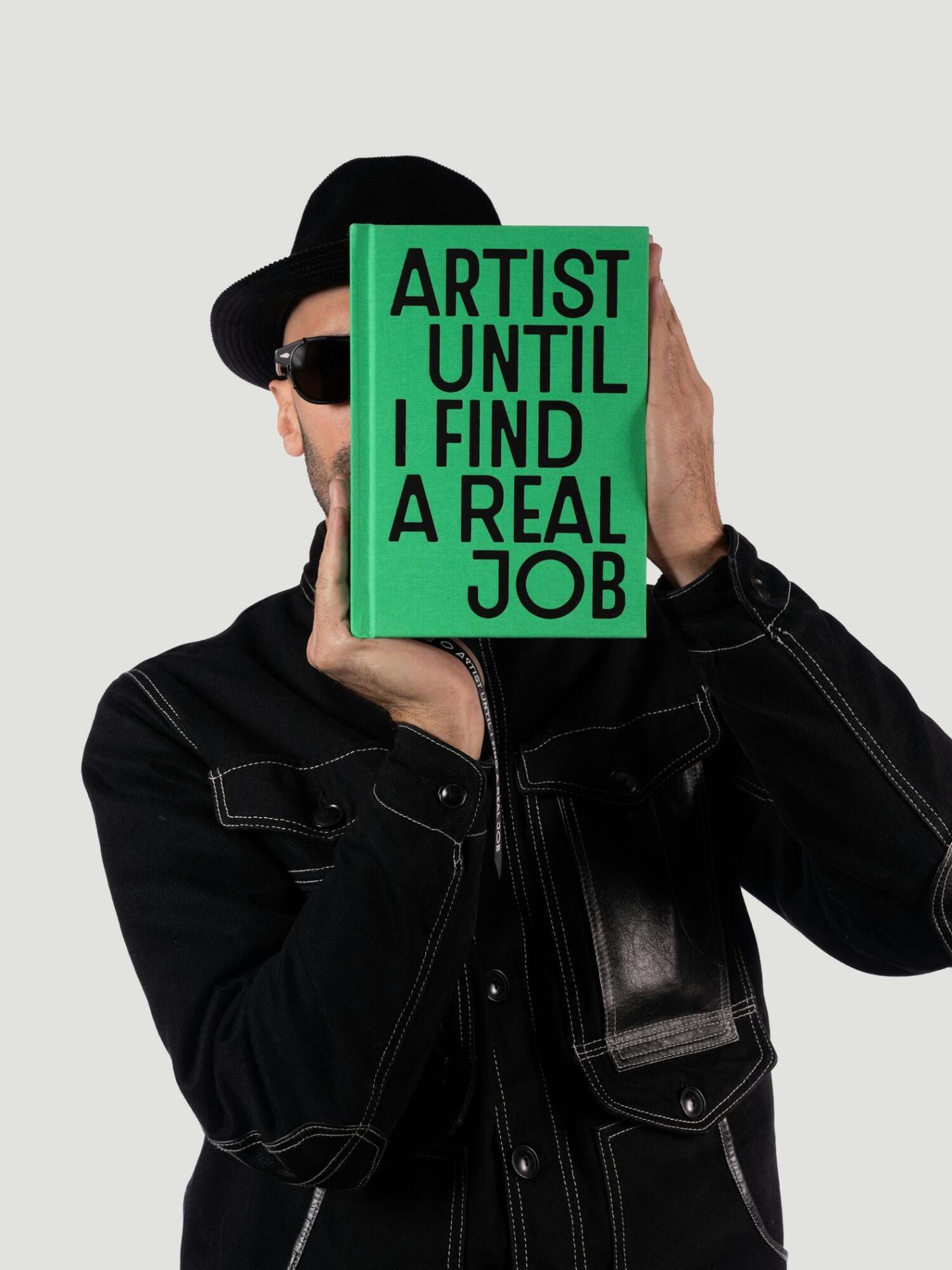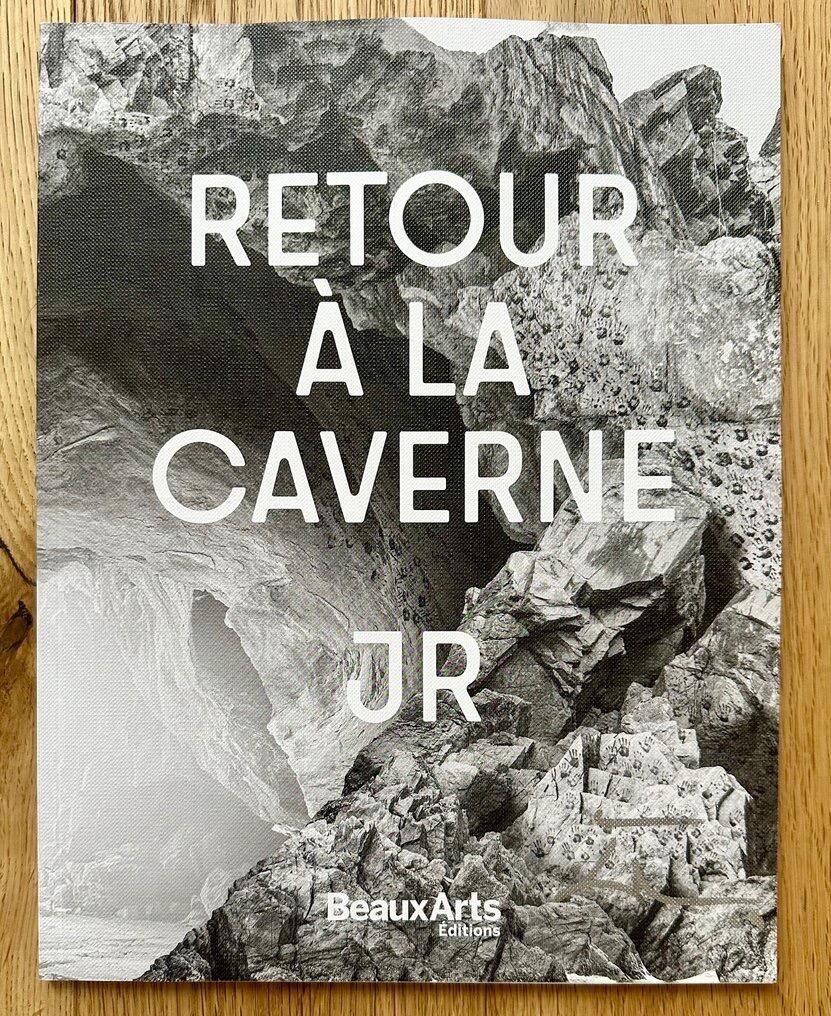
Schrift in Publikationen von JR (Artist)
Vermutlich eine Art Hausschrift für den Künstler – die Website sagt sie heißt »JR« (surprise!).
Die Frage ist von wem sie stammt und ob sie auf einem Retail-Font basiert ...
Die unterschiedlichen Varianten sind ja Konzept und technisch ist das ja auch kein Problem.
Arthur Alazard auf Instagram: »JR Type is a custom typeface designed with @h5paris for @atelierjr !«
Auf deren Website: »H5 gestaltet die Identität des Künstlers JR und seiner Online-Boutique Atelier JR. Unsere Antwort dreht sich um eine maßgeschneiderte Typografie, die von Emailleschildern und Buchstabenmalern inspiriert ist. Das berühmte Wort „Défense d’afficher loi du 29 juillet 1881“ (Verbot des Plakatierens, Gesetz vom 29. Juli 1881) wird echoartig dargestellt.
Die Darstellung des Auges, die in seiner Arbeit allgegenwärtig ist, ist ein zentrales Element unseres Vorschlags. Das stilisierte Auge, das zum Zeichen und dann zum Logo wurde, ersetzt den Punkt in seinem fotografischen Raster.«
Ich mag halt die minimal abgerundeten Ecke – die hat die Rauschen leider nicht.